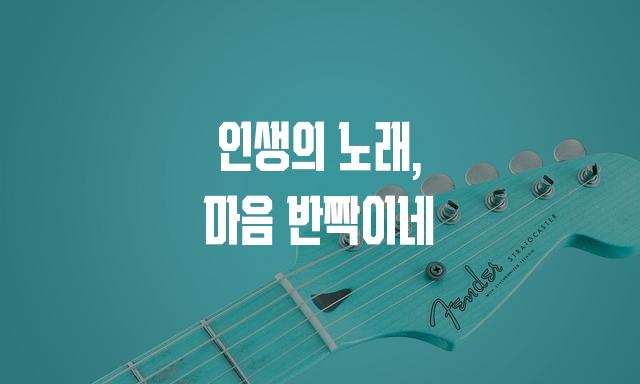
비트로 코어체는 주식회사 학산에서 제작한 제목용 폰트로, 꽉 찬 고딕 스타일과 장식적인 요소를 갖춘 두꺼운 글꼴입니다. 강렬하고 눈에 띄는 디자인으로, 메시지를 강조하고자 할 때 탁월한 선택입니다.
비트로 코어체은(는)
기본 고딕, 두꺼운 스타일, 굵은 고딕, 장식 스타일, 단단함, 별모양/패턴, 길고/크고 계열의 생김새를 가지고 있으며
로고 디자인, 웹/앱 디자인, 브랜딩 등에서 자주 활용되며, 효과적인 메시지 전달에 적합합니다.
이 폰트는 광고/마케팅, 크리에이티브, 기술/IT 분야에 잘 어울리며,
현대적, 세련된, 전문적인 느낌을 담고 있는 것이 특징입니다.
이 폰트와 유사한 폰트로는 나눔바른고딕, 스포카 한 산스, 고딕A1 등이 있어요. 함께 비교해 보시면 좋습니다!